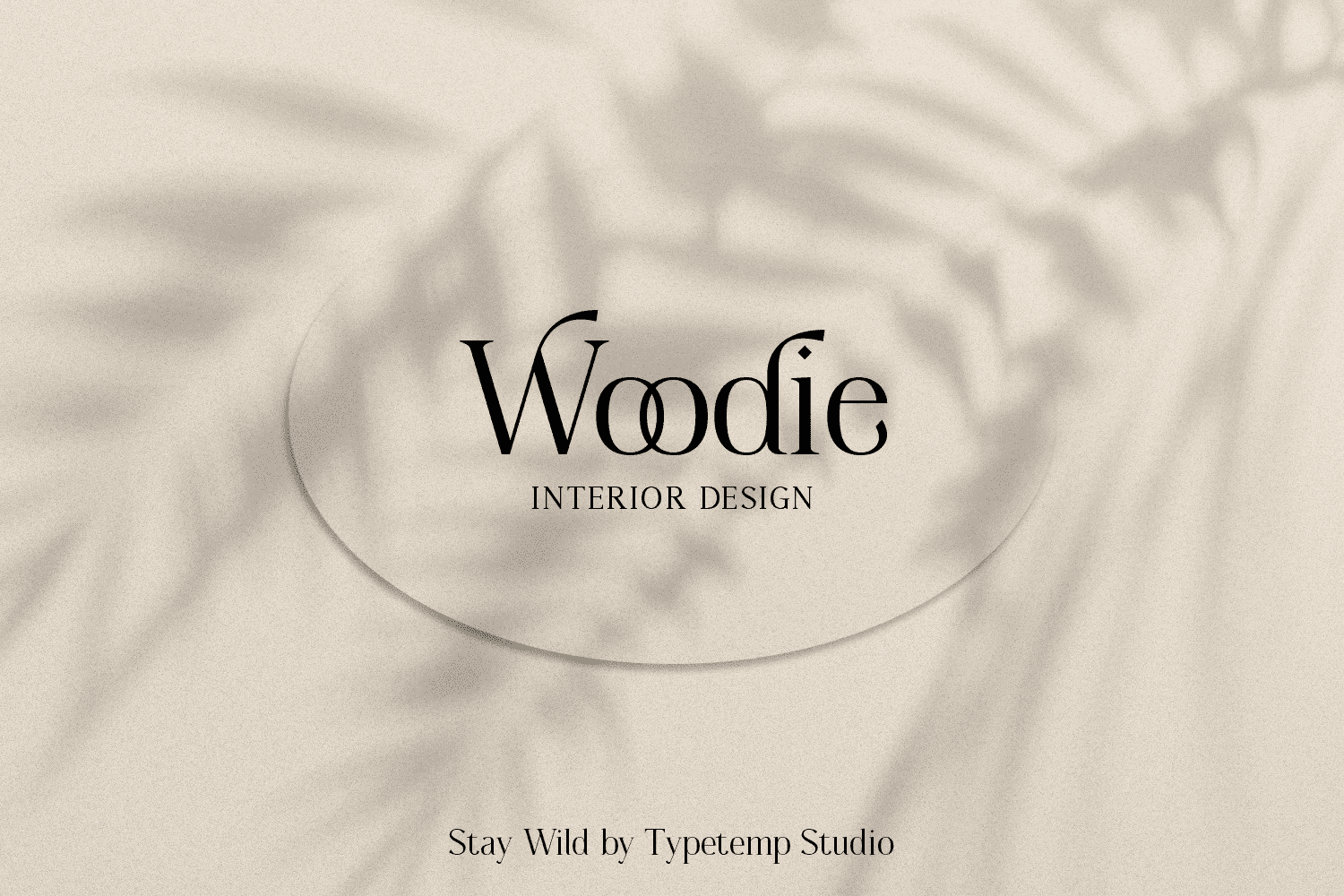
[Creativefabrica] Woodie Font (2021)
Название: Woodie Font (2021)
[Creativefabrica] Woodie Font (2021)
Woodie
- классный и элегантный шрифт с засечками.
Влюбитесь в его невероятно универсальный стиль и используйте его для создания эффектных дизайнов!